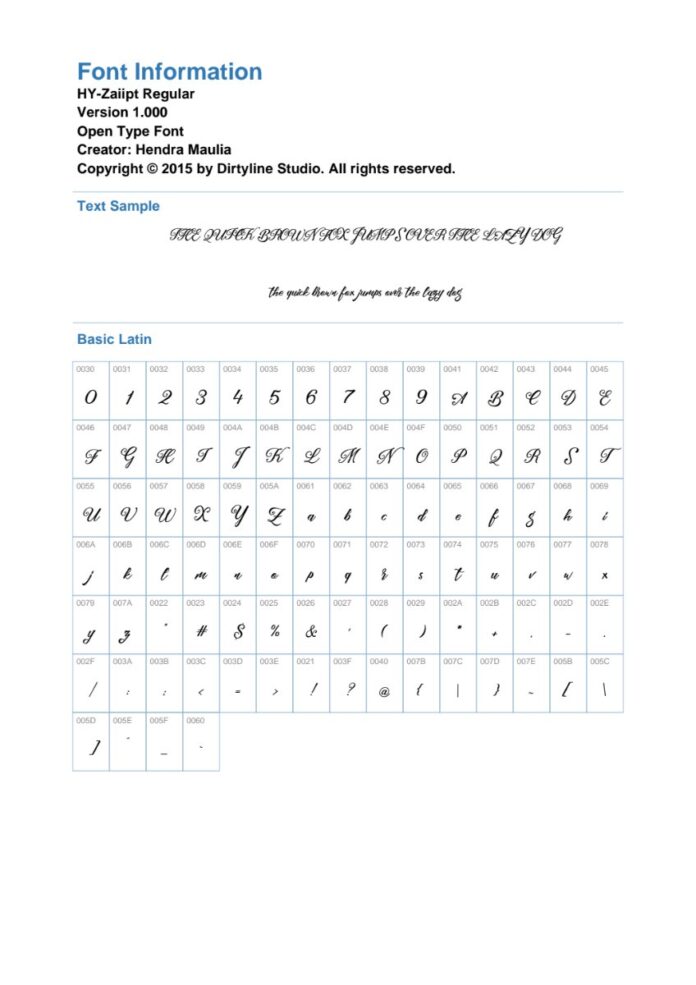
Font HY-Zaiipt: Nét Chữ Bay Bổng
Font HY-Zaiipt: Nét Chữ Bay Bổng. Khám phá font HY-Zaiipt, một kiểu chữ viết tay mềm mại và bay bổng, lý tưởng cho các thiết kế cần sự tinh tế và cá nhân hóa. Tải ngay tại Poster.vn để tạo điểm nhấn độc đáo cho dự án của bạn.
Trong thế giới thiết kế đồ họa, việc lựa chọn font chữ phù hợp có thể tạo nên sự khác biệt lớn, biến một thiết kế đơn giản thành một tác phẩm nghệ thuật đầy cảm xúc. Font HY-Zaiipt là một trong những lựa chọn tuyệt vời dành cho những ai đang tìm kiếm sự mềm mại, bay bổng và cá tính trong từng nét chữ. Tại Poster.vn, chúng tôi tự hào mang đến cho bạn tài nguyên font chữ chất lượng cao này, giúp bạn thỏa sức sáng tạo và nâng tầm các dự án của mình.
Giới Thiệu Chung Về Font HY-Zaiipt
Font HY-Zaiipt là một kiểu chữ viết tay (script font) được thiết kế với phong cách thanh lịch và uyển chuyển. Mỗi ký tự đều được chăm chút tỉ mỉ, mang đến cảm giác như được viết bằng tay một cách tự nhiên và duyên dáng. Với những đường nét mềm mại, các ký tự nối liền nhau tạo nên một dòng chảy liền mạch, rất phù hợp cho các thiết kế cần sự tinh tế và lãng mạn.
Font này đặc biệt thích hợp cho các dự án như thiệp mời, logo thương hiệu cá nhân, tiêu đề tạp chí, bao bì sản phẩm, hay bất kỳ thiết kế nào muốn truyền tải sự ấm áp, gần gũi và độc đáo. Sự linh hoạt của HY-Zaiipt cho phép nó kết hợp hài hòa với nhiều phong cách thiết kế khác nhau, từ cổ điển đến hiện đại.
Đặc Điểm Nổi Bật Của Font HY-Zaiipt
• Phong cách viết tay: Mô phỏng chân thực nét chữ viết tay, mang lại cảm giác cá nhân hóa và độc đáo.
• Thanh lịch và duyên dáng: Các đường nét mềm mại, uyển chuyển tạo nên vẻ đẹp tinh tế và sang trọng.
• Dễ đọc: Mặc dù là font viết tay, HY-Zaiipt vẫn đảm bảo tính dễ đọc, giúp thông điệp của bạn được truyền tải rõ ràng.
• Đa dụng: Phù hợp với nhiều loại hình thiết kế khác nhau, từ in ấn đến kỹ thuật số.
Ứng Dụng Của Font HY-Zaiipt Trong Thiết Kế
Font HY-Zaiipt có thể được ứng dụng rộng rãi trong nhiều lĩnh vực thiết kế khác nhau, mang lại hiệu quả thẩm mỹ cao:
1. Thiết Kế Thương Hiệu và Logo
Đối với các thương hiệu muốn xây dựng hình ảnh gần gũi, cá tính và độc đáo, HY-Zaiipt là một lựa chọn lý tưởng. Nó có thể được sử dụng để thiết kế logo cho các cửa hàng thời trang, tiệm bánh, studio chụp ảnh, hoặc các dịch vụ cá nhân hóa. Nét chữ mềm mại sẽ giúp thương hiệu của bạn trở nên đáng nhớ và thu hút hơn.
2. Thiệp Mời và Ấn Phẩm Sự Kiện
Trong các thiết kế thiệp cưới, thiệp sinh nhật, hay thiệp mời sự kiện, HY-Zaiipt sẽ mang đến sự lãng mạn và trang trọng. Nét chữ bay bổng của nó giúp tạo ra một ấn tượng khó quên cho người nhận, thể hiện sự chu đáo và tinh tế của người gửi.
3. Bao Bì Sản Phẩm
Các sản phẩm thủ công, mỹ phẩm tự nhiên, hoặc thực phẩm cao cấp thường cần một font chữ thể hiện sự tinh tế và chất lượng. HY-Zaiipt có thể giúp làm nổi bật tên sản phẩm hoặc các thông điệp quan trọng trên bao bì, tạo cảm giác cao cấp và độc đáo.
4. Thiết Kế Website và Mạng Xã Hội
Để tạo điểm nhấn cho tiêu đề bài viết, trích dẫn, hoặc các banner quảng cáo trên website và mạng xã hội, HY-Zaiipt là một công cụ mạnh mẽ. Nó giúp thu hút sự chú ý của người xem và làm cho nội dung trở nên sống động hơn.
5. Sách và Tạp Chí
Trong thiết kế bìa sách, tiêu đề chương, hoặc các trích dẫn đặc biệt trong tạp chí, HY-Zaiipt có thể tạo ra một phong cách riêng biệt, giúp cuốn hút độc giả ngay từ cái nhìn đầu tiên.
Hướng Dẫn Sử Dụng Font HY-Zaiipt Hiệu Quả
Để tận dụng tối đa vẻ đẹp của font HY-Zaiipt, bạn có thể tham khảo một số mẹo sau:
• Kết hợp với font Sans-serif: Để đảm bảo tính dễ đọc cho phần nội dung chính, hãy kết hợp HY-Zaiipt (dùng cho tiêu đề hoặc điểm nhấn) với một font sans-serif đơn giản và rõ ràng.
• Kích thước phù hợp: Font viết tay thường đẹp nhất khi được sử dụng ở kích thước lớn hơn một chút so với font chữ thông thường, giúp các đường nét uyển chuyển được hiển thị rõ ràng.
• Màu sắc: HY-Zaiipt có thể kết hợp tốt với nhiều bảng màu khác nhau. Hãy thử nghiệm với các màu sắc tương phản hoặc màu pastel để tạo ra hiệu ứng mong muốn.
• Khoảng cách chữ: Điều chỉnh khoảng cách giữa các chữ (kerning) nếu cần để đảm bảo sự hài hòa và dễ đọc, đặc biệt là khi sử dụng cho các từ ngắn hoặc logo.
Font HY-Zaiipt có dễ đọc không?
Mặc dù là font viết tay, HY-Zaiipt được thiết kế để đảm bảo tính dễ đọc, đặc biệt khi được sử dụng ở kích thước phù hợp và kết hợp với các font chữ khác.